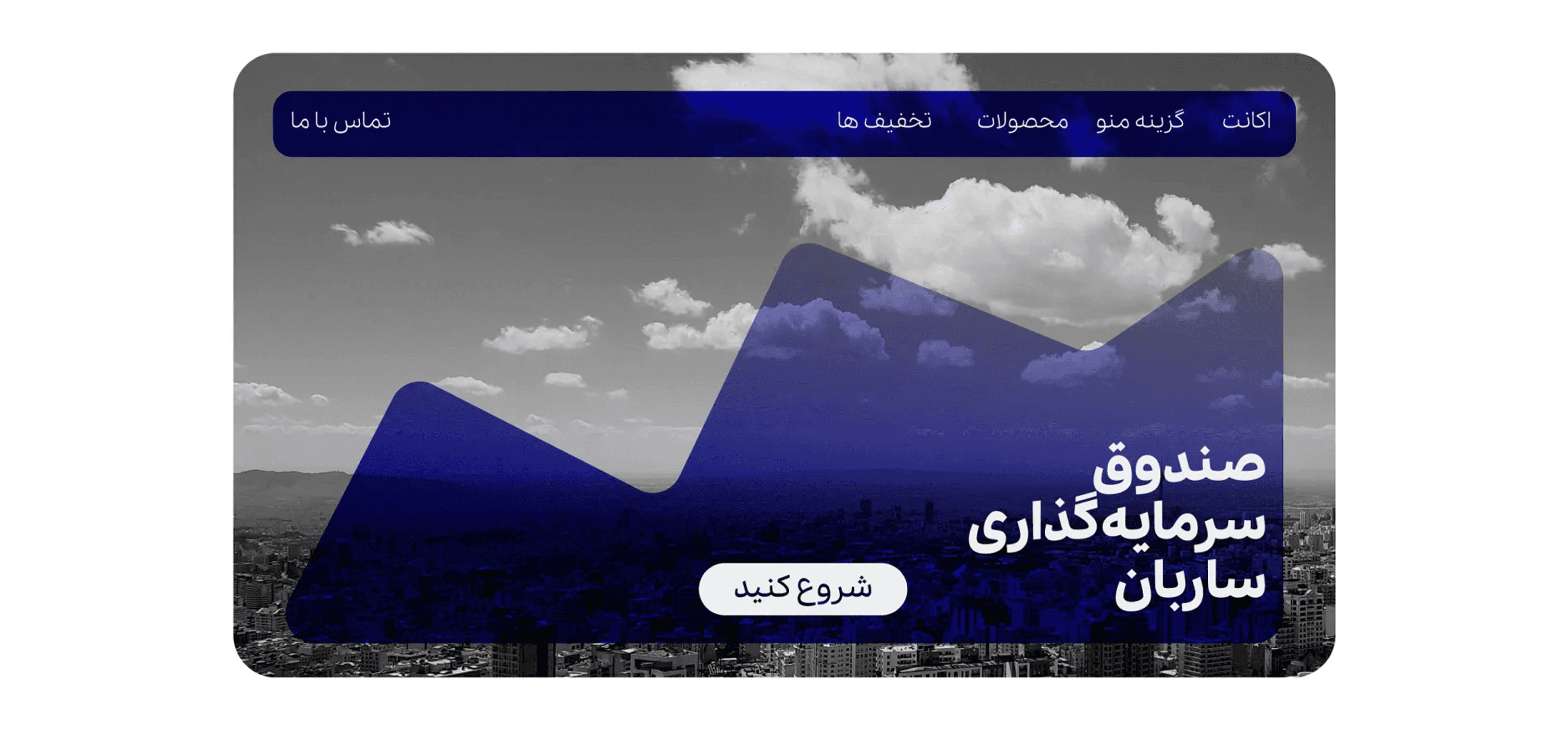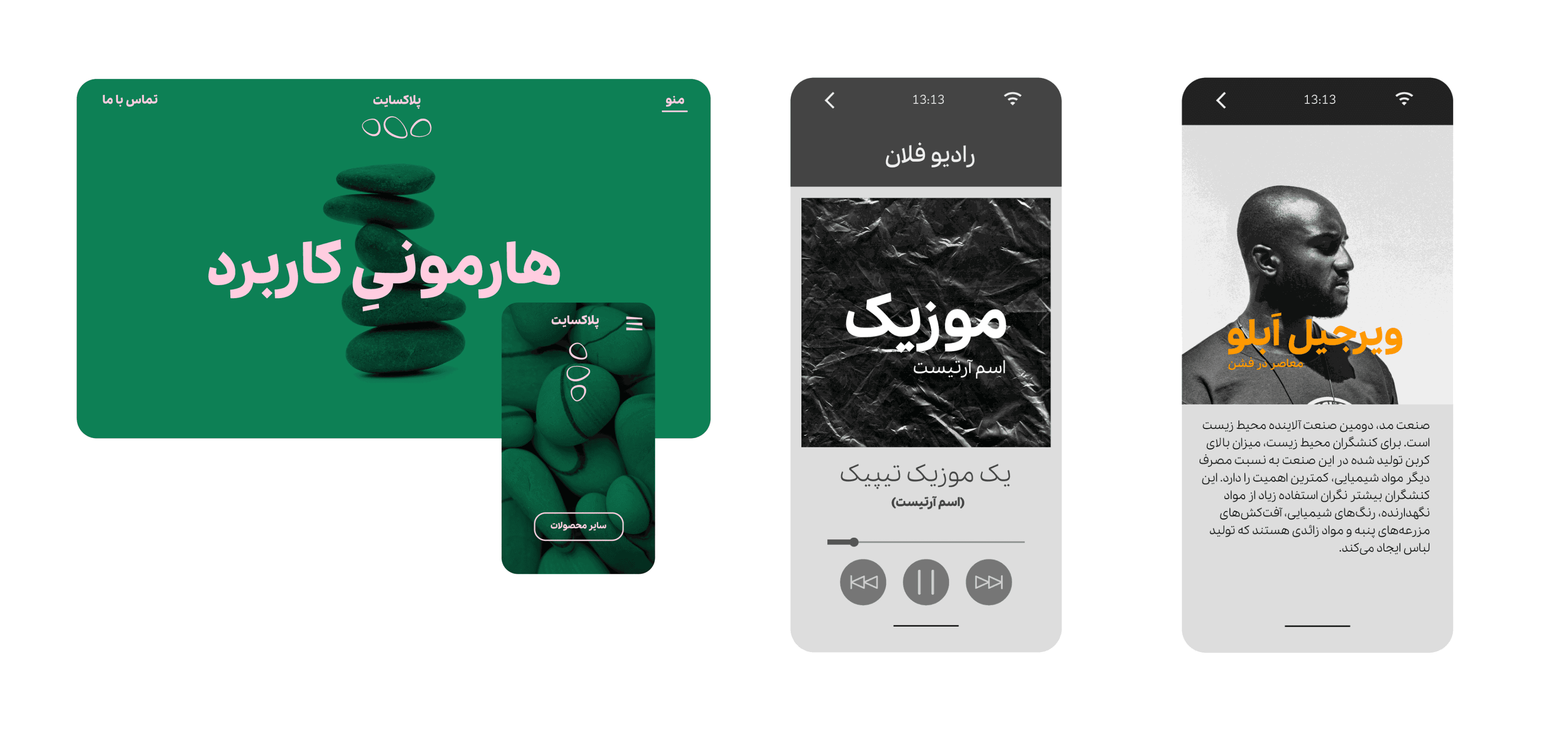
فونت پلاک از نوع سنس است. با تنوع ضخامت حداقل، منحنیهای بسیار، دندانهها و چشمهای بزرگ و فشردگی در ارتفاع سطرها. همهٔ این ویژگیها باعث میشود پلاک یک فونت مدرن، روان و سیال، دارای حس انسانی و در عین حال دارای حروف واضح و خوانا در اندازه ریز باشد.